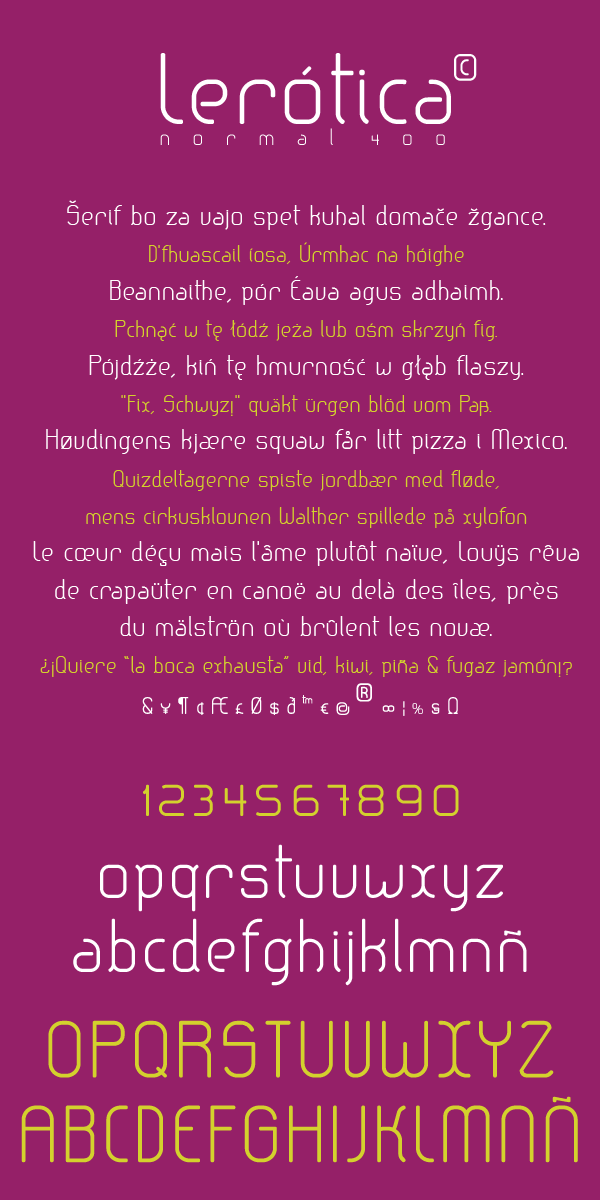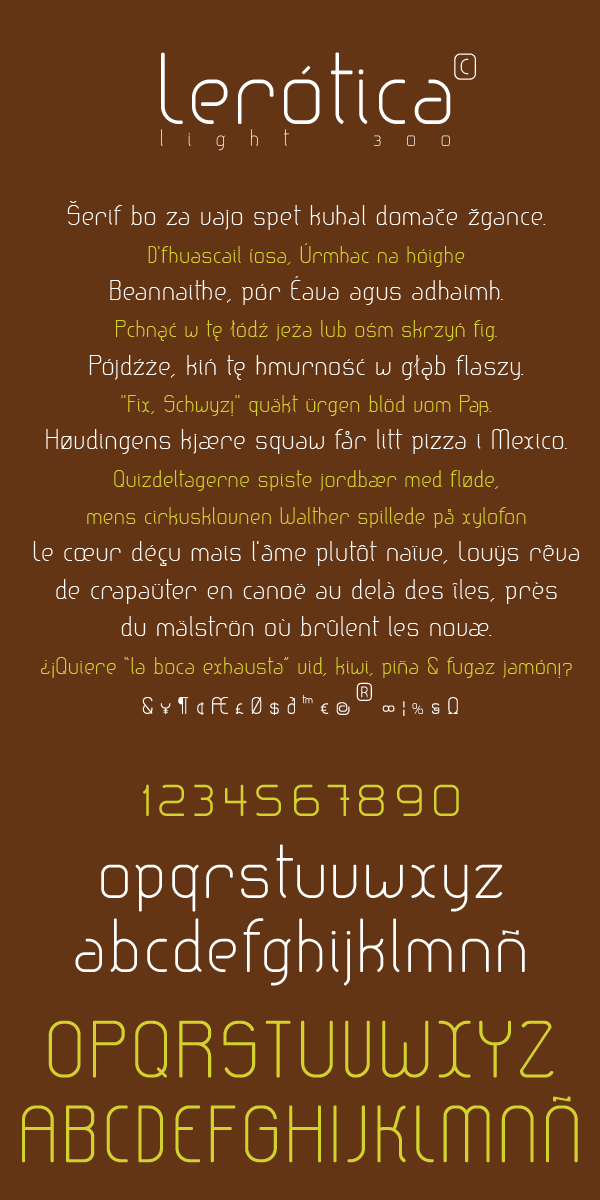
Esta es una tipografía sin serif con acabados redondeados y semi condensada, dibujada sobre una rejilla de 100 x 100 pt. y una proporción de 8/10, surgió inspirada en el trabajo de un nuevo logotipo para la marca de relojes «eroticlock», de ahí su nombre.Estoy acabando los detalles de la familia completa con varios pesos: Extra light, Light, Normal, Medium, Demi bold, Bold y Extra bold, me gustaría conocer tu opinión sobre el diseño y comportamiento de la fuente.
La fuente contiene todos los caracteres del latín, con lo cual sirve para cualquier idioma hablado en Europa. Como comentaba en el post sobre el desarrollo de mi primera fuente: La chata tipografía & webfont gratis, hay cosas que no controlo y cosas que no se en el diseño tipográfico, por esta razón he dado una vuelta de tuerca en la construcción de esta nueva fuente, he simplificado, con respecto a la anterior, el dibujado de las curvas, he trabajado sobre una cuadrícula de 100 pt, una anchura de astas de 100 pt y una proporción de 8/10 todo esto con el fin de hacer lo más profesional posible esta nueva tipografía, en definitiva ensayo error, porque he buscado por internet y apenas he encontrado información válida para controlar las proporciones de una fuente. Si sabes de algo que me pueda ayudar será siempre bienvenido.
Lo que si ha marcado la diferencia con la anterior tipografía ha sido el tiempo de desarrollo, mucho menor, gracias a la experiencia adquirida en la construcción de La chata; el espaciado de caracteres y el kerning, ha sido, esta vez, una tarea menos tediosa, pues el hecho de la geometría de esta fuente y el espaciado calculado con números proporcionales relativos a las proporciones de la fuente ha facilitado el manejo del kerning y con un tercio de pares de letras con respecto a la chata he conseguido el ritmo y la armonía en el texto de párrafo.
Estoy trabajando en diferentes pesos de la tipografía, para decidir finalmente el aumento o disminución de los glifos, también para calcular que caracteres o terminaciones debo cambiar para adaptarse a cada nuevo peso, tengo el trabajo muy encaminado y próximamente incluiré toda la familia para descarga.